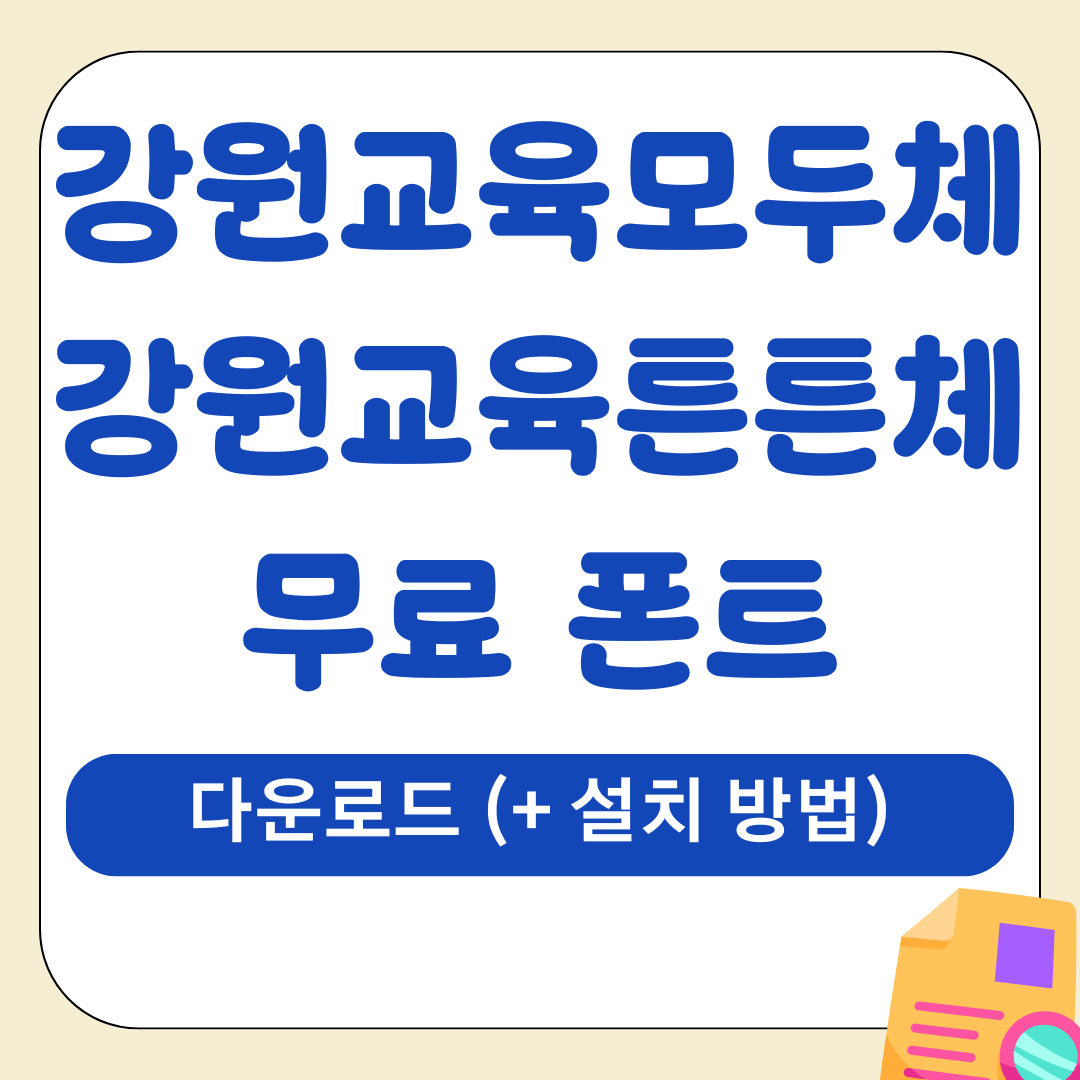
1. 강원교육 폰트 개요
강원교육청이 배포한 강원교육모두체와 튼튼체는 누구나 무료로 사용할 수 있는 고품질 글꼴입니다. 개인·상업적 활용이 가능하며, 교육청의 정체성을 반영한 디자인으로 가독성과 활용도가 뛰어납니다.
| 항목 | 강원교육모두체 | 강원교육튼튼체 |
|---|---|---|
| 디자인 특징 | 깔끔하고 편안한 가독성 | 두껍고 힘 있는 강조형 디자인 |
| 활용도 | 보고서, 본문 텍스트, 온라인 콘텐츠 | 제목, 강조 문구, 프레젠테이션 |
4. 강원교육 서체 활용 팁
- 강원교육모두체 → 블로그 본문, 보고서, 발표 자료에서 깔끔한 분위기 연출
- 강원교육튼튼체 → 포스터 제목, 유튜브 자막, 광고 배너에서 강한 임팩트 표현
- 썸네일, 교육 자료, 카드뉴스 등 시각적 콘텐츠 제작에 적합
- 색상 대비가 뚜렷해 온라인/오프라인 콘텐츠 모두 활용 가능